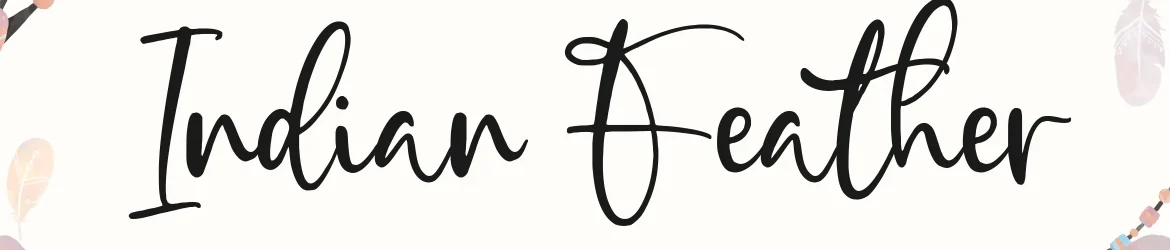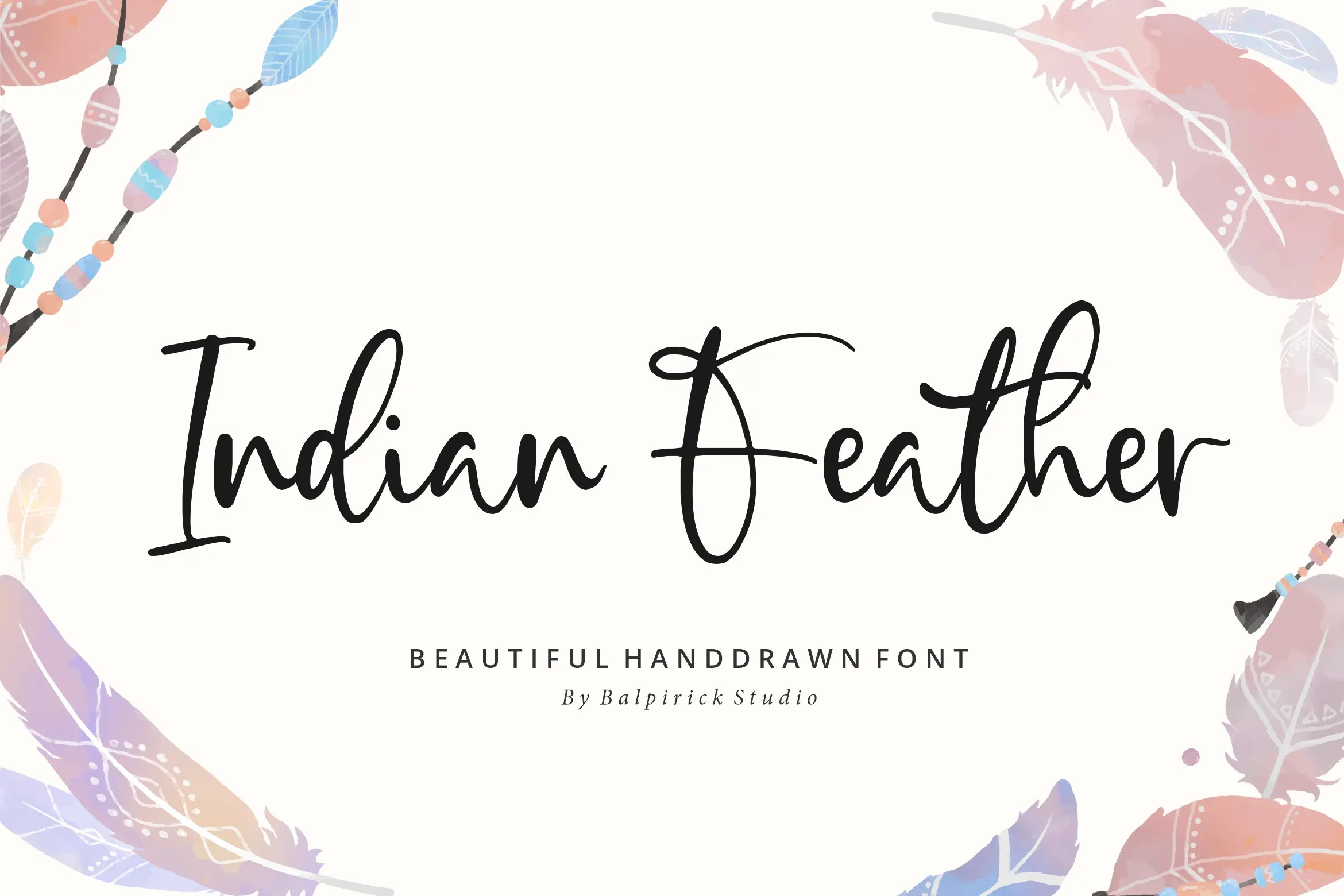
Indian Feather Font
A fonte ‘Indian Feather Font’ é uma elegante tipografia feita para quem busca um toque sofisticado em seus projetos de design. Inspirada nas deliciosas técnicas de escrita feitas à mão, ela parece dançar sobre a linha base do papel, conferindo um brilho sofisticado e romântico ao seu trabalho. Perfeita para adicionar uma nota especial às criações digitais dos seus projetos mais inusitados, esta fonte é ideal para quem valoriza os mínimos detalhes na arte visual. Sua origem no estilo de letra feito à mão e nas técnicas de escrita do chamado ‘Indian Feather’ permitem que a tipografia seja tanto versátil quanto delicada. Seja em um projeto gráfico ou uma criação digital, a ‘Indian Feather Font’ é uma escolha perfeita para adicionar um toque único e elegante ao seu trabalho.